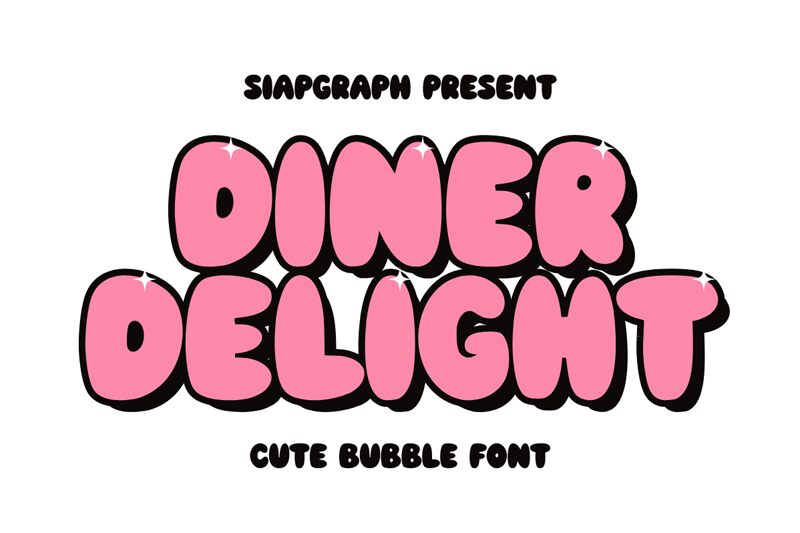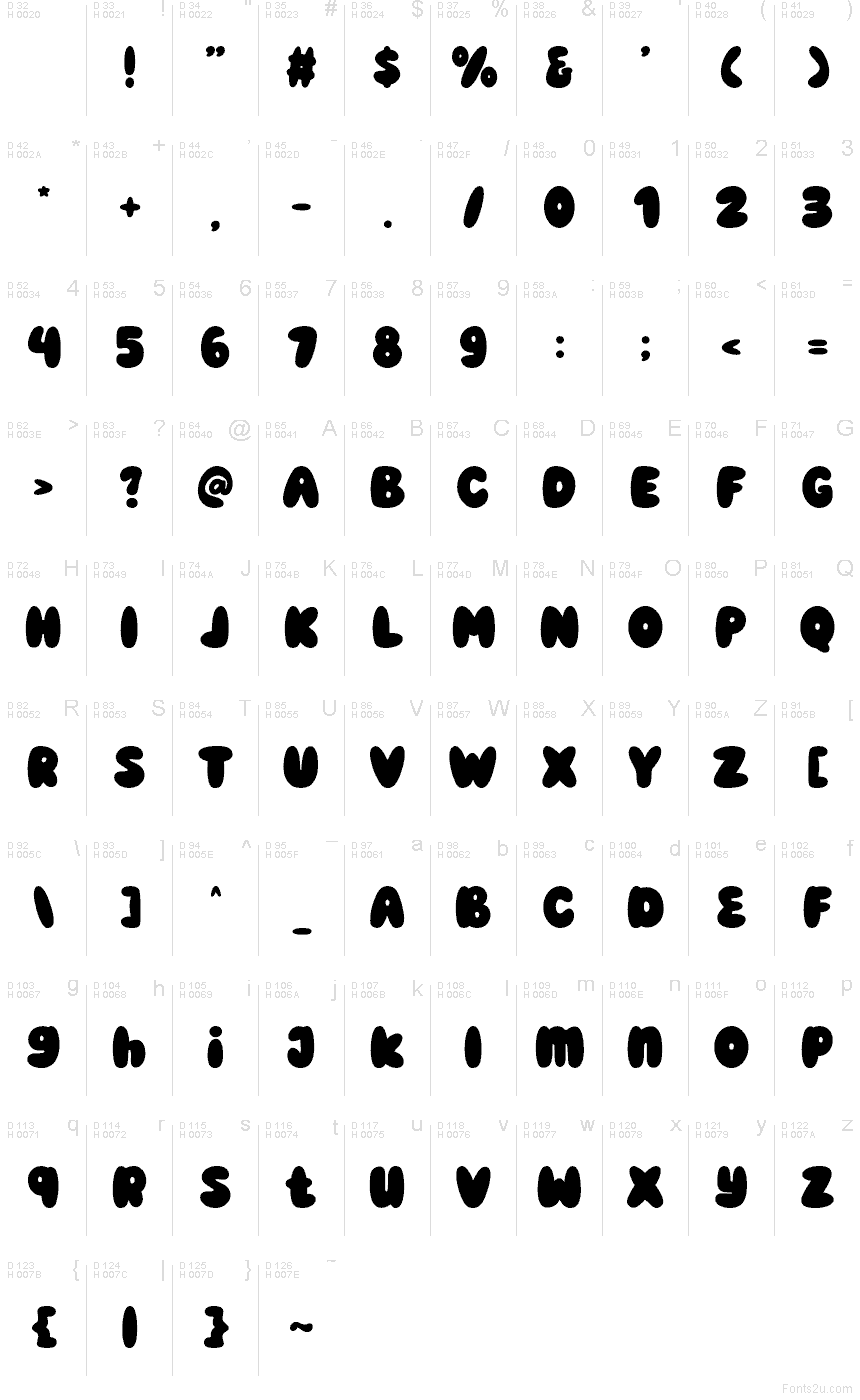
Diner Delight
Diner Delight от SIAPGRAPH STUDIO - это бесплатный мультяшный дисплейный шрифт, построенный на крупных, пухлых формах, которые напоминают мягкие надувные буквы. Скругленный силуэт сохраняется во всем наборе, придавая шрифту дружелюбную и «прыгучую» текстуру, которая скорее ассоциируется с формованными вывесками или буквами из пенопласта, чем со стандартными акцидентными гарнитурами.
Этот объемный и компактный вид отлично подходит для детских плакатов, упаковки закусок, брендинга веселых кафе, приглашений на дни рождения и заголовков в социальных сетях, где нужен радостный и яркий голос. Шрифт лучше всего проявляет себя в коротких заголовках и логотипах, где широкие изгибы создают эффектную графическую форму без необходимости в лишнем декоре.